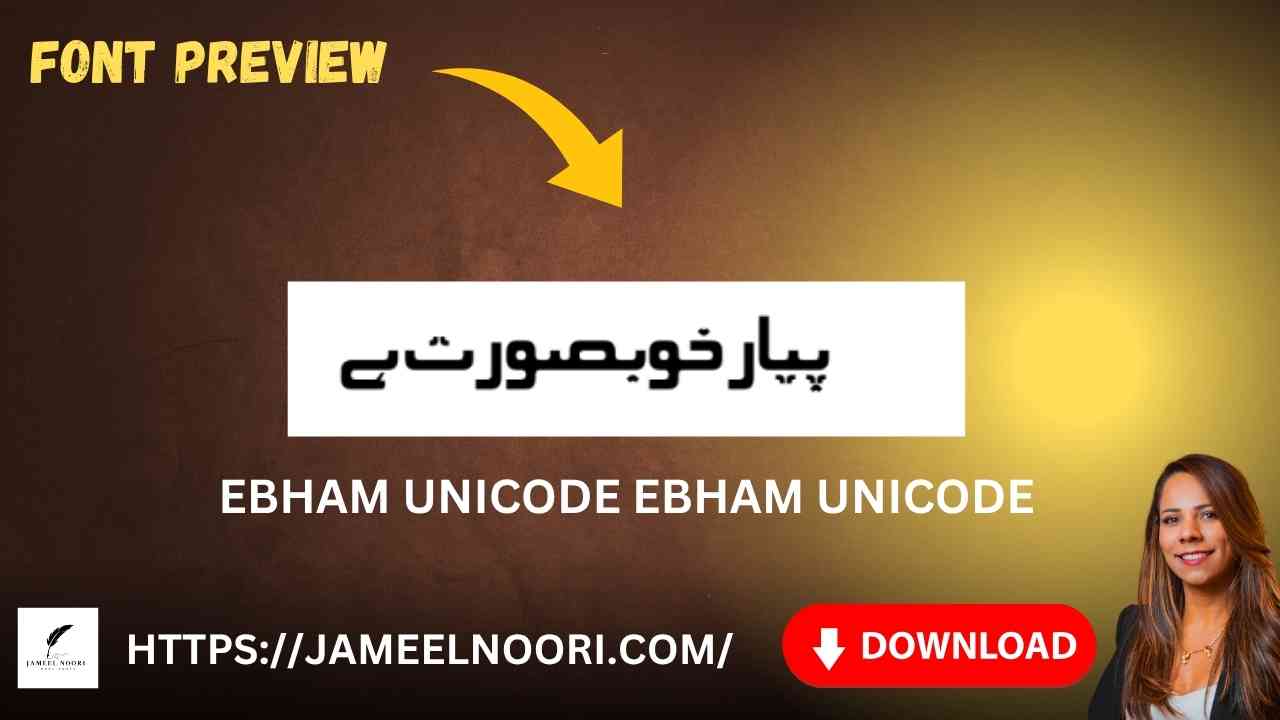
Agar aap ek simple aur Unicode-based Urdu font ki talash mein hain, to Download Urdu Font Ebham Unicode zarur try karein. Ye font TrueType format me available hai aur Pakistan ke users ke liye specially Urdu typing ko asaan banata hai.
Ebham Unicode Font key Features
| Font Name | Ebham Unicode |
| Supported Language | Urdu, Arabic |
Uses of Download Urdu Font Ebham Unicode in Pakistan
Pakistan ke kai cities jaise Lahore, Karachi, aur Islamabad me Urdu type karne ke liye log Unicode fonts ka use karte hain. Ebham Unicode un fonts me se aik hai jo beginner level users ke liye useful hai.
Use Cases:
- Urdu blog writing
- Educational worksheets
- Digital notes
- Social media captions
EWhy Choose Download Urdu Font Ebham Unicode – Affordable Unicode Option
Jab baat ho Unicode fonts ki, to Ebham Unicode aik affordable aur simple option hai un users ke liye jo basic readability aur compatibility chahtay hain. Is font ka design minimal hai, lekin typing ke liye enough hai.
Why Choose This Font?
- Unicode supported
Is Ebham Unicode Font Reliable?
Agar aap ek simple, Unicode-based, aur free Urdu font dhoond rahe hain jo Windows aur Android dono platforms pe kaam kare, to Download Urdu Font Ebham Unicode zarur karein. Ye ek acha option hai beginners ke liye jo Urdu me type karna seekh rahe hain.
What is Ebham Unicode font?
It is a basic TrueType Urdu Unicode font designed for general Urdu typing.
Is Ebham Unicode a good font for professional documents?
It is more suitable for basic and personal use; professional users may prefer more polished fonts.